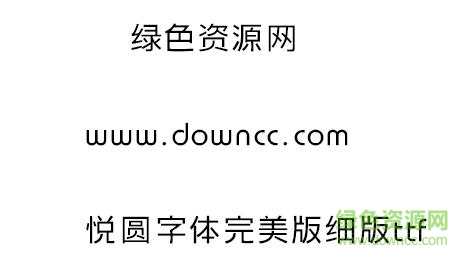
悅圓字體完美版細(xì)版ttf將讓你能夠感受到最不錯的二次元英文拼寫體驗,讓你輕松的獲得最佳的使用效果,在二次元界中輸入此款字體將獲得十分不錯的效果哦,快來綠色資源網(wǎng)下載吧!
這款字體在于它的英文字體十分的不錯,使用的時候?qū)⒏惺艿胶芎玫囊曈X效果,在眾多的二次元場合中使用都能夠達(dá)到優(yōu)質(zhì)的使用體驗!